El mundo está lleno de letras por todos los lados y conviene estar muy atentos para inspirarse en cada elemento que veamos para crear nuestros propios letterings.
Yo siempre recomiendo que, por la calle, vayáis muy atentos a los rótulos de los comercios, especialmente los antiguos, así como aquellos que están rotulados a mano, que es el verdadero origen del lettering actual. También os animo a que os fijéis en cualquier diseño de carteles de eventos, exposiciones, películas, conciertos y demás, ya que son una fuente inagotable de letterings que podéis luego hacer a mano.
Hay muchos más elementos, como los diseños de portadas de discos, especialmente vinilos antiguos, y otros en los que quizás no nos fijamos tan a menudo, como los vinilos frases. Estos vinilos decorativos, que normalmente vemos en cristales de escaparates o en paredes de comercios, bares, restaurantes y viviendas que visitamos, también están llenos de letras en los que inspirarse, así que muy atentos y atentas a sus diseños, que os vamos a mostrar algunos ejemplos.
Combinación de distintas letras
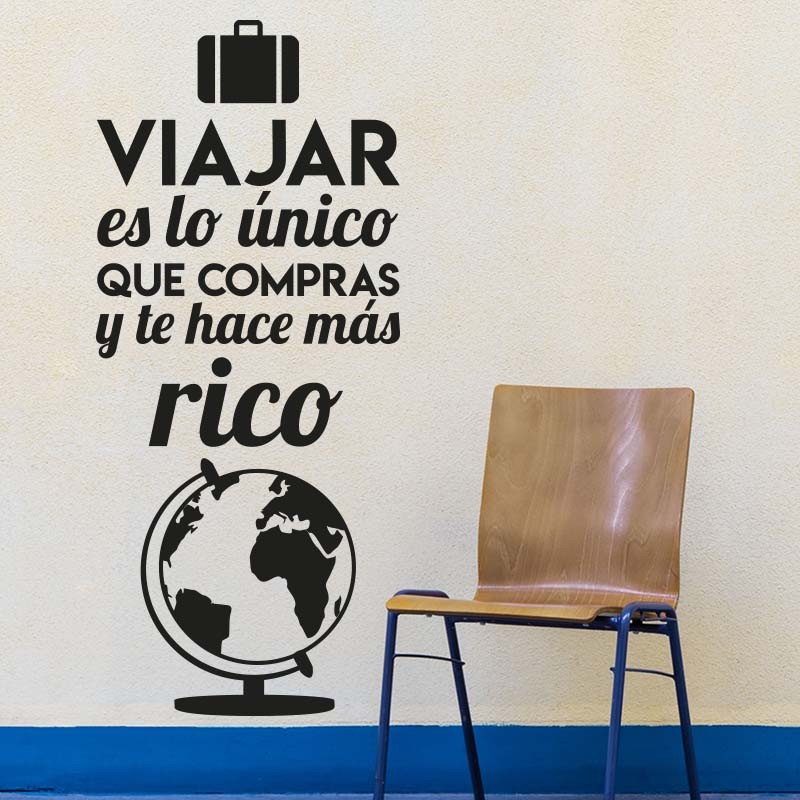
Una de las cosas que podemos observar y aprender de estos vinilos es que, en las frases largas, suelen utilizar más de un tipo de letra, pero que combinan muy bien entre sí. Por ejemplo, en esta que vemos en la imagen, combinan mayúsculas sin serifas o sin remates con un tipo de letra script, de las que simulan estar escritas a mano, lo cual es un total acierto. Además, hay que tener en cuenta que es una composición rectangular y vertical con las palabras centradas y que, para ayudar a darle esta forma, tiene dos elementos gráficos que le ayudan: una maleta y una bola del mundo.
Letras clásicas con remates
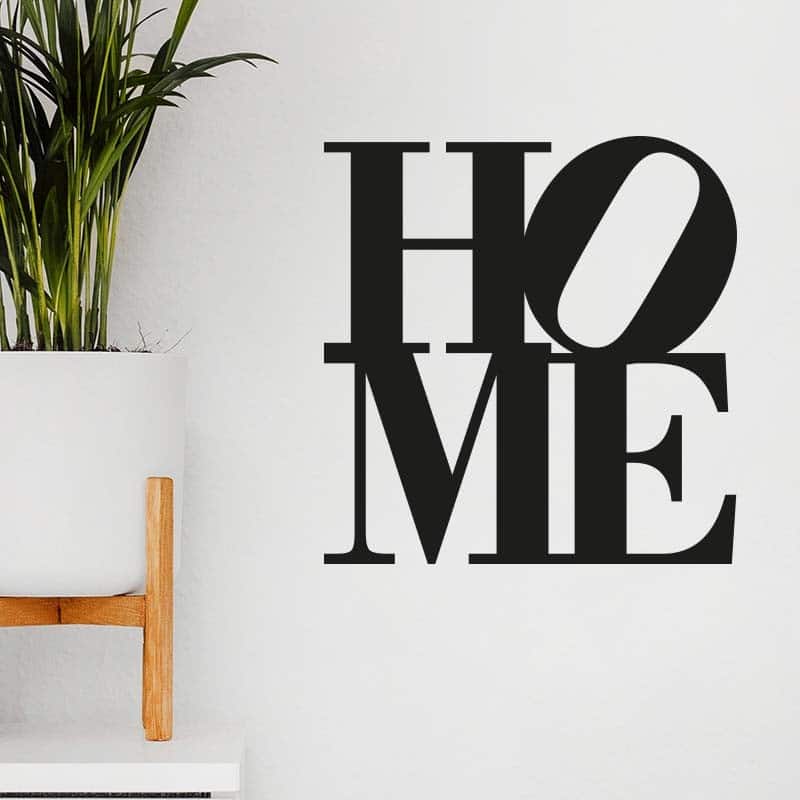
En otros vinilos de pared podemos ver otro estilo de letras más clásicas y más sobrias, sin combinar con otras. Se trata de aquellos que tienen letras con remates o con serifas, como las romanas, para entendernos. Que sean sólidas no quiere decir que no sean modernas o que no podamos aportar un toque original. Por ejemplo, en el vinilo de la imagen se juega con poner unas letras encima de las otras formando un bloque con la palabra «Home», al mismo tiempo que se rompe un poco el diseño con la «O» inclinada, lo que le da dinamismo y originalidad. Es al mismo tiempo elegante y moderno.
Ya hemos hablado en este blog de la composición, así como de dibujar banners o pancartas, así como lazos y otras decoraciones, para que el lettering gane en calidad y en complejidad. En este vinilo vemos como han querido dar un acento o resaltar al autor de la frase, en este caso, Albert Einstein, enmarcando su nombre en un banner. Es una buena decisión y es recomendable cuando queremos recalcar algo importante de la frase. También podemos observar que hay frases que se complementan con decoraciones laterales, como puntos, e incluso alguna línea decorativa en el interlineado. Queda genial.
Composición en un bloque rectangular
De este vinilo de pared nos interesan varias cosas. Primero, que tiene 6 tipos de letras distintos en una misma frase y quedan bien juntos, lo cual parece imposible a priori, pero que funciona. Lo segundo y más destacable, que tiene una composición en un bloque rectangular casi perfecto, conseguida gracias los tipos de letra utilizado, a fondos en negativo, a rectángulos y a algunas decoraciones añadidas cuando la frase no llega al punto que tiene que llegar. Es un diseño óptimo.
Juego con los espacios en negativo
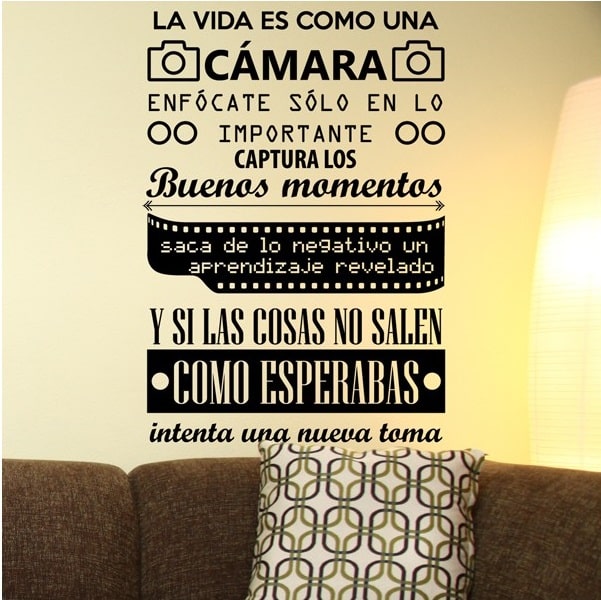
Finalmente, queremos recalcar en este vinilo el diseño en negativo de algunas partes de la frase, aunque es verdad que en el vinilo anterior ya lo hemos visto. De nuevo, vemos 6 tipos de letras distinas que combinan bien entre ellas y con decoraciones que tienen que ver con la frase, relacionadas con las cámaras de fotos y la fotografía. Puesto que utiliza un negativo para hacer lettering negativo, es decir, con el fondo negro y las letras en blanco, nos parece que riza el rizo. Es genial.